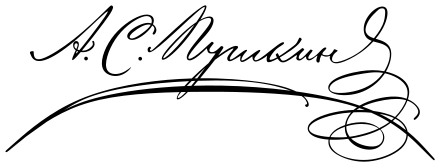
Шрифт по имени Pushkin — Год Литературы
Вряд ли 21 год назад, накануне торжеств, посвященных 200-летию великого русского поэта, широкая общественность обратила внимание на появление нового шрифта Pushkin, созданного на основе почерка Александра Сергеевича.
Популярность способствовала возникновению второй версии шрифта. Это была скорее группа шрифтов, объединенных одним названием: Pushkin… Однако обо всем по порядку.
1999 год. Ребята из Тверского КСП ВНИИСВ готовили к выпуску очередной номер клубного журнала «Слух и Голос». В год юбилея Пушкина это было музыкальное путешествие по его стихотворениям, повестям и сказкам. Журнал выходил (и выходит до сих пор) два раза в год и готовился с особенной тщательностью. Основное внимание отдавалось текстам песен, иллюстрациям и, конечно же, шрифту – в каждом номере он был новым.
Именно в этот момент у
Эмиля Якупова – главного редактора журнала и по совместительству директора шрифтовой компании «ПараТайп» – возникла идея создать шрифт на основе почерка поэта.
По задумке шрифт должен был использоваться в заголовках.
Благо к тому времени у главреда и его коллег уже сформировался технологический опыт подготовки шрифтов на основе почерка. Довольно быстро удалось найти достаточное количество автографов, и рабочий вариант был собран всего за месяц.
Первая версия распространилась настолько широко, что, казалось, шрифт используют уже в быту. Например, текст песни «Вальс-бостон», нанесенный на бутылку водки с тем же названием, совсем не соответствовал авторскому представлению о шрифте.
Но популярность все же принесла пользу: спустя несколько лет при создании «Альбома стихов Пушкина» издатели столкнулись с необходимостью иметь несколько оцифрованных вариантов почерка, отличающихся как минимум по годам. Ими планировалось набрать тексты стихотворений, для которых не сохранилось автографов.
Альбом так и не вышел, но разработку новой версии шрифта это не остановило. Еще несколько лет анализа и поисков привели к группе начертаний, разных по характеру почерка – от мелкого, но достаточно разборчивого до более размашистого, с несколькими вариациями по насыщенности.
Шрифты того времени нельзя было наполнить современными контекстуальными подстановками и стилистическими наборами знаков. Но с помощью небольшого количества альтернатив и вариантов дополнительных концевых форм всё же удалось оживить и разнообразить текст при наборе.
Возможно, что в будущем увидит свет расширенная и дополненная новыми свойствами и альтернативами версия. Но это будет уже совсем другая история.
Серия шрифтов «Пушкин» разработана для фирмы «ПараТайп» в 1999–2004 годах (дизайнер Геннадий Фридман). Шрифт создан на основе автографов А.С. Пушкина. В комплект знаков шрифта включены альтернативные варианты некоторых букв, характерные для почерка поэта. Шрифт «Пушкин Скрипт» в двух начертаниях основан на рукописях 1815 года и содержит комплект знаков для набора помимо русского на основных западноевропейских языках. «Пушкин Один» создан на основе наиболее аккуратно написанных документов. «Пушкин Два» имитирует вариант мелкого, но тем не менее достаточно разборчивого почерка.«Пушкин Три» также имеет два начертания разных насыщенностей и имитирует автографы, отличающиеся размашистым написанием букв. Шрифты серии «Пушкин 1, 2, 3» содержат только буквы русского алфавита. В дополнение к ним спроектирован шрифт «Пушкин Франс» в западноевропейской комплектации.
«Пушкин Три» также имеет два начертания разных насыщенностей и имитирует автографы, отличающиеся размашистым написанием букв. Шрифты серии «Пушкин 1, 2, 3» содержат только буквы русского алфавита. В дополнение к ним спроектирован шрифт «Пушкин Франс» в западноевропейской комплектации.